Seit längerer Zeit beobachte ich das bemerkenswerte Programm der Edition Büchergilde (vgl. u. a. Fontblog: 36 Versicherungsblüten, illustriert von Jens Bonnke). In dem Frankfurter Verlag erscheinen wunderbar ausgestattete Bücher, zeitgemäß Illustriert und lesefreundlich typografiert.
Die Büchergilde (Gutenberg) wurde 1924 als Buchgemeinschaft vom Bildungsverband der deutschen Buchdrucker auf Initiative seines Vorsitzenden Bruno Dreßler in Leipzig gegründet. In der Tradition der deutschen Arbeiterbewegung stehend, ermöglichte sie ärmeren Leuten durch preiswerte Bücher den Zugang zu Bildung und Kultur. Nach dem Krieg baute der Sohn des Gründers, Helmut Dreßler, die Büchergilde in Frankfurt am Main wieder auf. Bis zu seinem Tode im Dezember 1974 engagierte sich Dreßler für handwerklich gut gemachte, illustrierte Bücher. Diese Tradition setzt sich bis heute fort.
Im Herbst 2002 wurde der eigenständige Verlag Edition Büchergilde ausgegliedert, um Eigenproduktionen auch auf dem freien Buchmarkt anzubieten. Seitdem erscheinen in dem jungen Verlag Belletristik, Sachbuch sowie die Künstleredition »Die Bibliothek von Babel« mit Umschlagillustrationen von Bernhard Jäger. Seit Herbst 2008 gibt der Ilija Trojanow in der Edition Büchergilde die Reihe »Weltlese – Lesereisen ins Unbekannte« heraus.
Die neuste Veröffentlichung erscheint zum 90. Todestag der neuseeländischen Kurzgeschichten-Autorin Katherine Mansfield. Sie ist als Meisterin der Short Story in die Literaturgeschichte eingegangen ist. Beneidet von ihrer Zeitgenossin Virginia Woolf, war sie Vorbild großer Autoren wie F. Scott Fitzgerald und Ernest Hemingway. 1909 verbrachte Katherine Mansfield einigeMonate in einer Pension im bayerischen Bad Wörishofen. Hier verfasste sie ein Dutzend messerscharfer Porträts und funkelnde Gesellschaftsskizzen, die 1911 unter dem Titel »In einer deutschen Pension« erschienen und sie berühmt machten.
In Mansfields Erzählungen tummeln sich auffällig fröhliche Witwen neben verunsicherten jungen Ehefrauen, auch der Teller voller Fleisch zur Mittagsstunde wie auch die alleingelassenen Kinder der so fürsorglichen Mütter stehen unter der Beobachtung der Autorin. Gekonnt stellt sie die Vorurteile und Stereotypen der englischen und deutschen Mentalität auf den Prüfstein. Aus dieser Distanz und der daraus entstehenden Spannung zwischen den Mentalitäten zu Beginn des 20. Jahrhunderts entsteht ein Panoptikum, das durch das Können Katherine Mansfields sowohl Gesellschaftskritik übt als auch Klischees auf den Prüfstand stellt. Elisabeth Schnack hat die Geschichten übersetzt und mit einem ausführlichen biografischen Essay versehen.
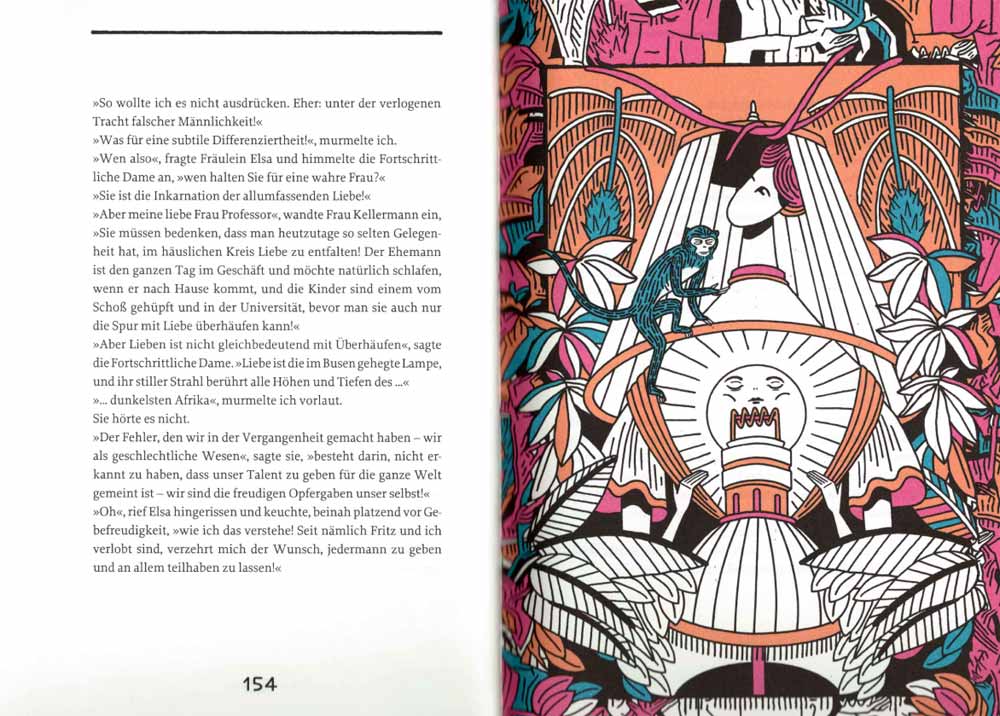
Bebildert wurden die scharfzüngigen Texte mit üppigen Tableaus der Künstlerin Joe Villion, in denen sie Jugendstil-Elemente mit surrealen Bildideen und lebendigen Farben mixt. Villion wurde 1981 in München geboren, wuchs in Italien und Griechenland auf und lebt seit 2001 in Berlin. Dort studierte sie bei Henning Wagenbreth an der Universität der Künste. 2010 gewann sie den Gestalterpreis der Büchergilde für »Zazie in der Metro«, für das sie 2011 ebenfalls das Ehrendiplom der Stiftung Buchkunst für ausgezeichnete buchkünstlerische Leistungen erhielt.
Das 280-seitige Hardcover-Buch wurde in drei Sonderfarben plus schwarz gedruckt. Es enthält 21 Abbildungen und kostet 24,95 €. Gesetzt ist es übrigens aus der wunderbaren Proforma Book (10,5 auf 15 Punkt), entworfen von Petr van Blokland. (ISBN 978-3-86406-020-5)
Und nicht zu vergessen die Typografische Bibliothek der Büchergilde in der von Klaus Detjen gestaltete und herausgegebene Bücher erscheinen.